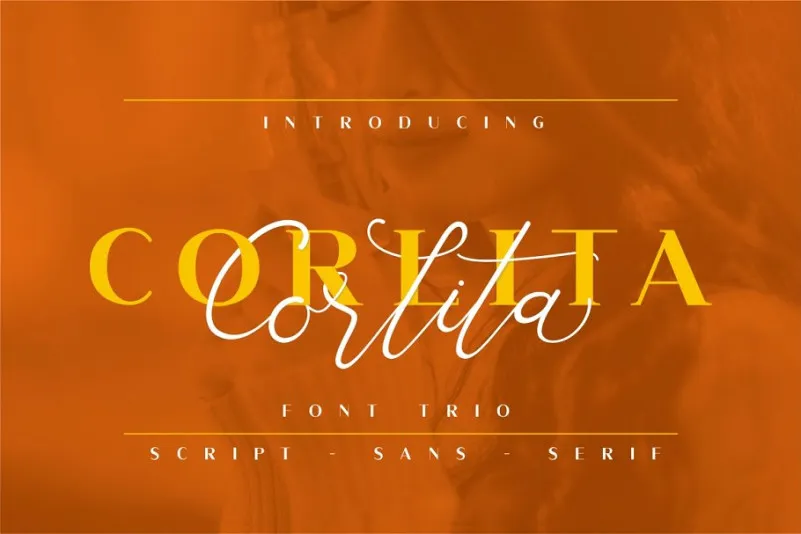
Aqui está a descrição no formato solicitado para download da font ‘Corlita Font Trio’: Olá! Estamos entusiasmados por apresentar Corlita Font Trio, nossa mais nova opção de fontes, um conjunto moderno e bonito que inclui uma mistura de tipografia do tipo, serif e script. Com suas linhas elegantes e modernas, você pode combinar as três para criar designs incríveis. A Corlita é perfeita tanto para criações de marca, como cartões de aniversário e embalagens luxuosas. Ela também adicionará um toque sofisticado a logotipos, posters e desenhos gráficos em papel. Além disso, sua versão script oferece liberdade criativa ideal para websites e materiais de envio digital. Corlita é uma fonte perfeita para projetos variados como embalagens, cartões de presente, identidade visual, sites e materiais publicitários. Estamos ansiosos para ajudá-lo a transformar seus ideias em realidade através desta bela e versátil fonte. Descubra o poder da Corlita agora!